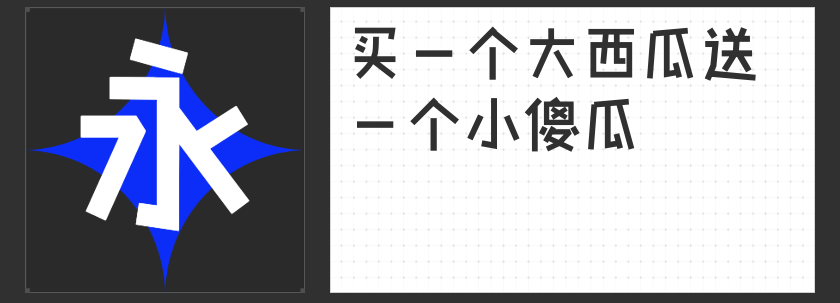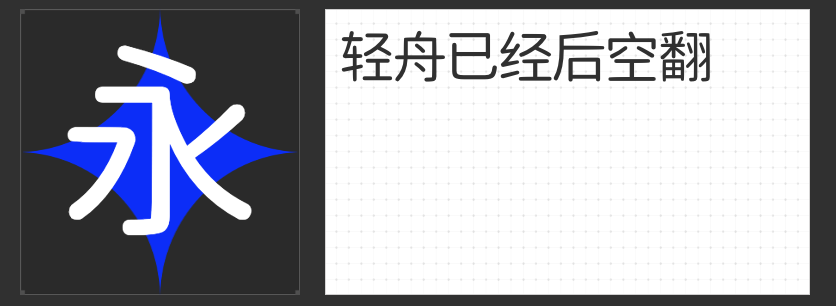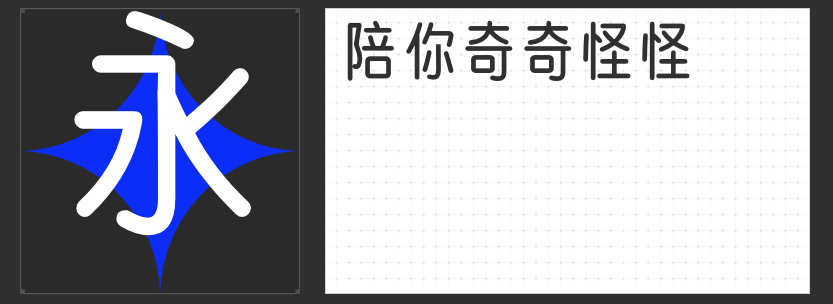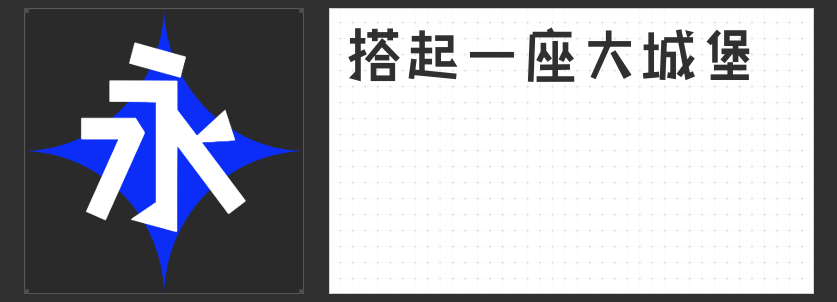
创意无限,探索字圈也字的黑体魅力
在字体的世界里,黑体以其独特的风格、鲜明的特点,成为了众多设计师和文案人员的心头好。今天,就让我们一起走进字圈也字的创意黑体世界,探索四款独具魅力的黑体字体。
首先登场的是“字圈也字呆板黑”。这款字体以其倾斜的姿态展现出动感和力量,仿佛每一个字母都在诉说着不屈与坚持。饱满而粗壮的线条,给人一种稳重和坚实的感觉,非常适合用于那些需要强调力量感和稳定性的设计作品中。
接下来是“字圈也字小积木体”。顾名思义,这款字体以积木为原型进行创意,横斜竖直、左低右高的字形结构,以及折笔处钝角与直角的巧妙结合,都让人感受到了它的独特魅力。笔画坚定、走向自信,这款字体仿佛在告诉我们:遵从自我内心,勇敢前行。
而“字圈也字幼稚黑体”则是一款极具时代印记的黑体。随着制字技术的精进,笔画端口的喇叭口形状装饰成为了它的独特之处。这款字体保留了黑体特有的规矩与方正之态,同时又在每一笔画的端口融入了喇叭口装饰,使得整体看起来端庄而不失活泼,非常适合用于那些需要展现童趣和活泼感的设计作品中。
最后,我们来看看“字圈也字万能黑体”。这款字体同样具有喇叭口形状的装饰,从字形来看依旧保留黑体特有的规矩与方正之态。它的出现,无疑为设计师们提供了更多的选择,无论是用于正式场合还是休闲场合,都能轻松驾驭。
总的来说,这四款字圈也字的创意黑体各有千秋,它们不仅丰富了我们的设计选择,更让我们在字里行间感受到了字体的独特魅力和无限可能。